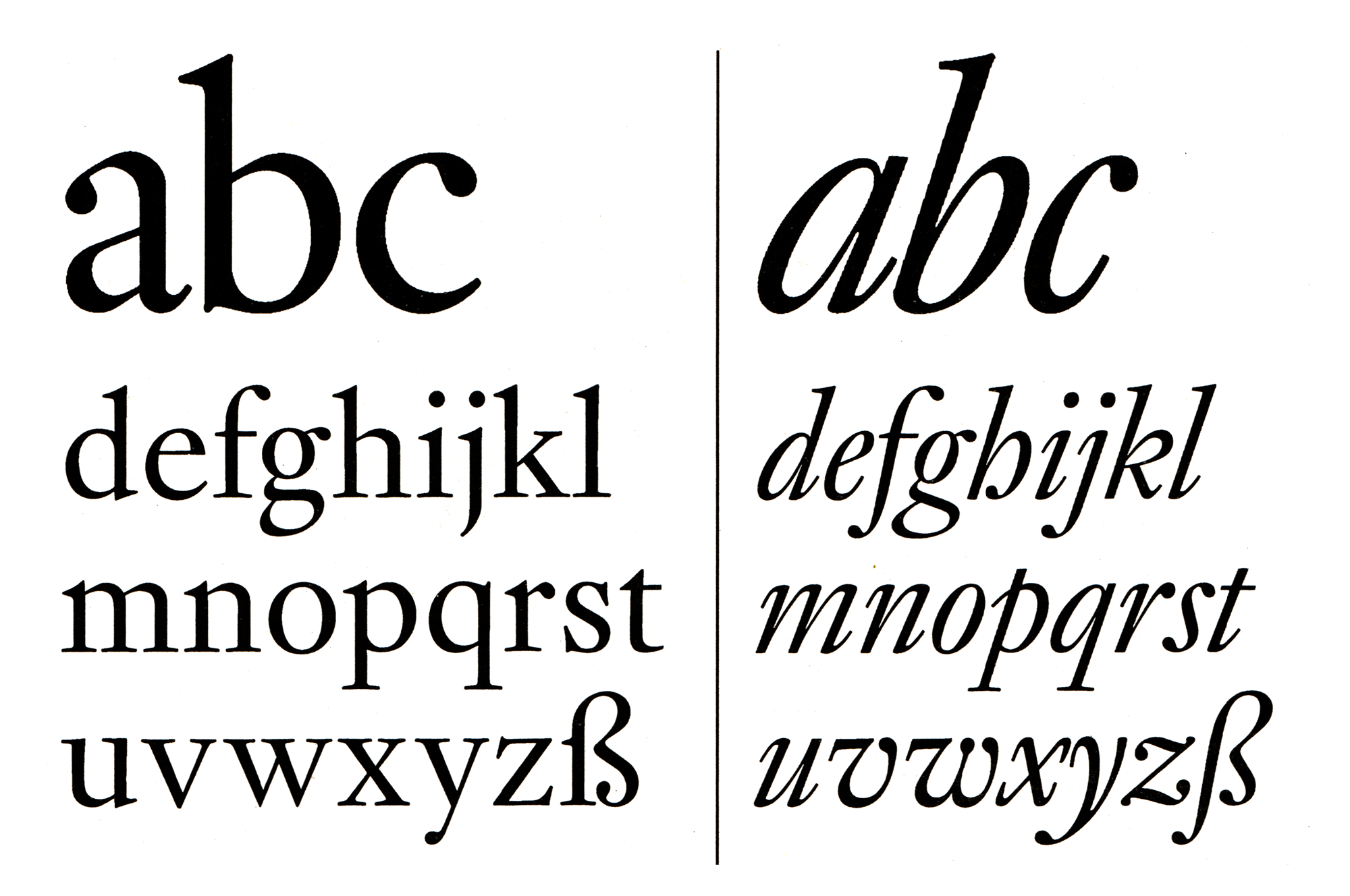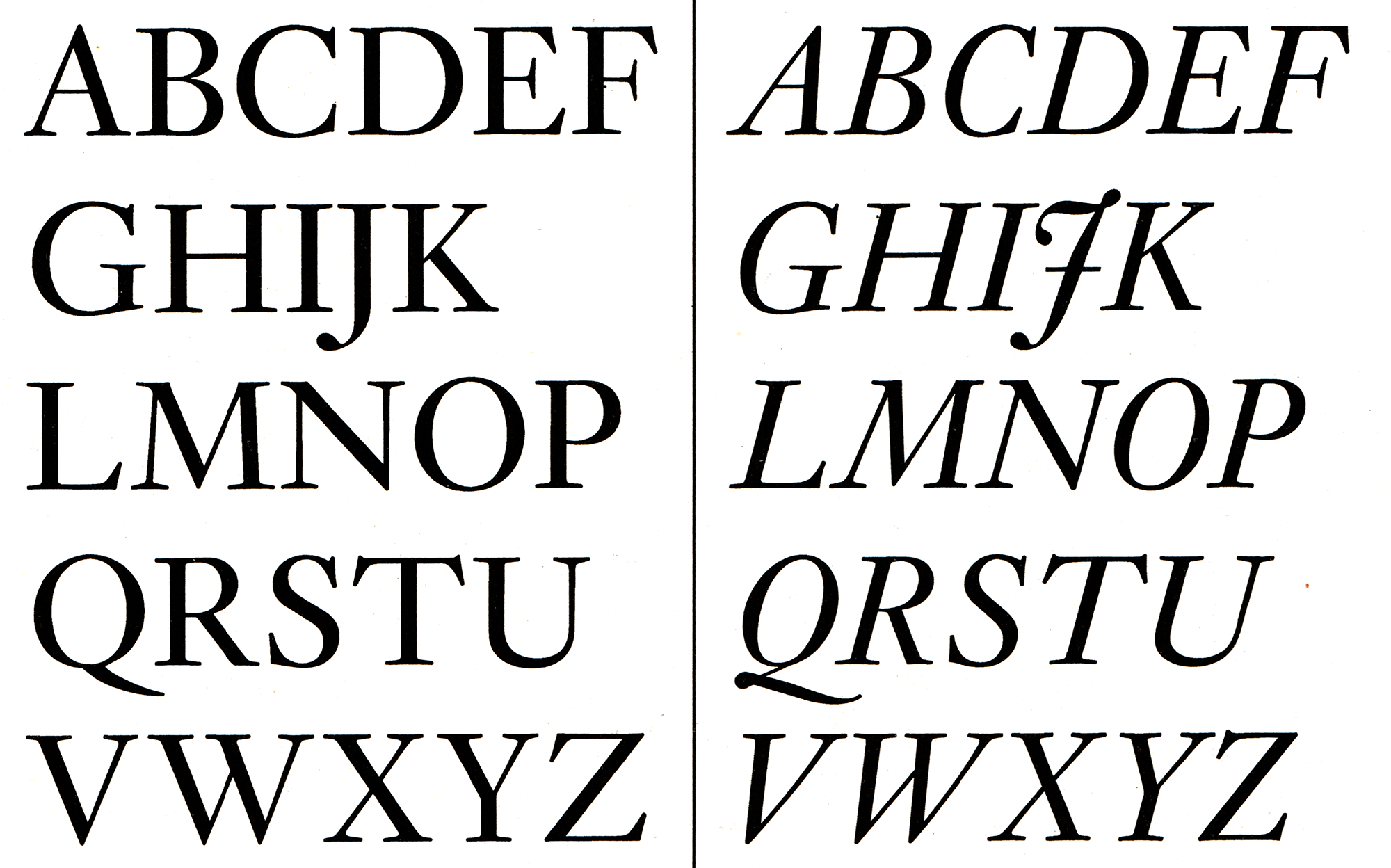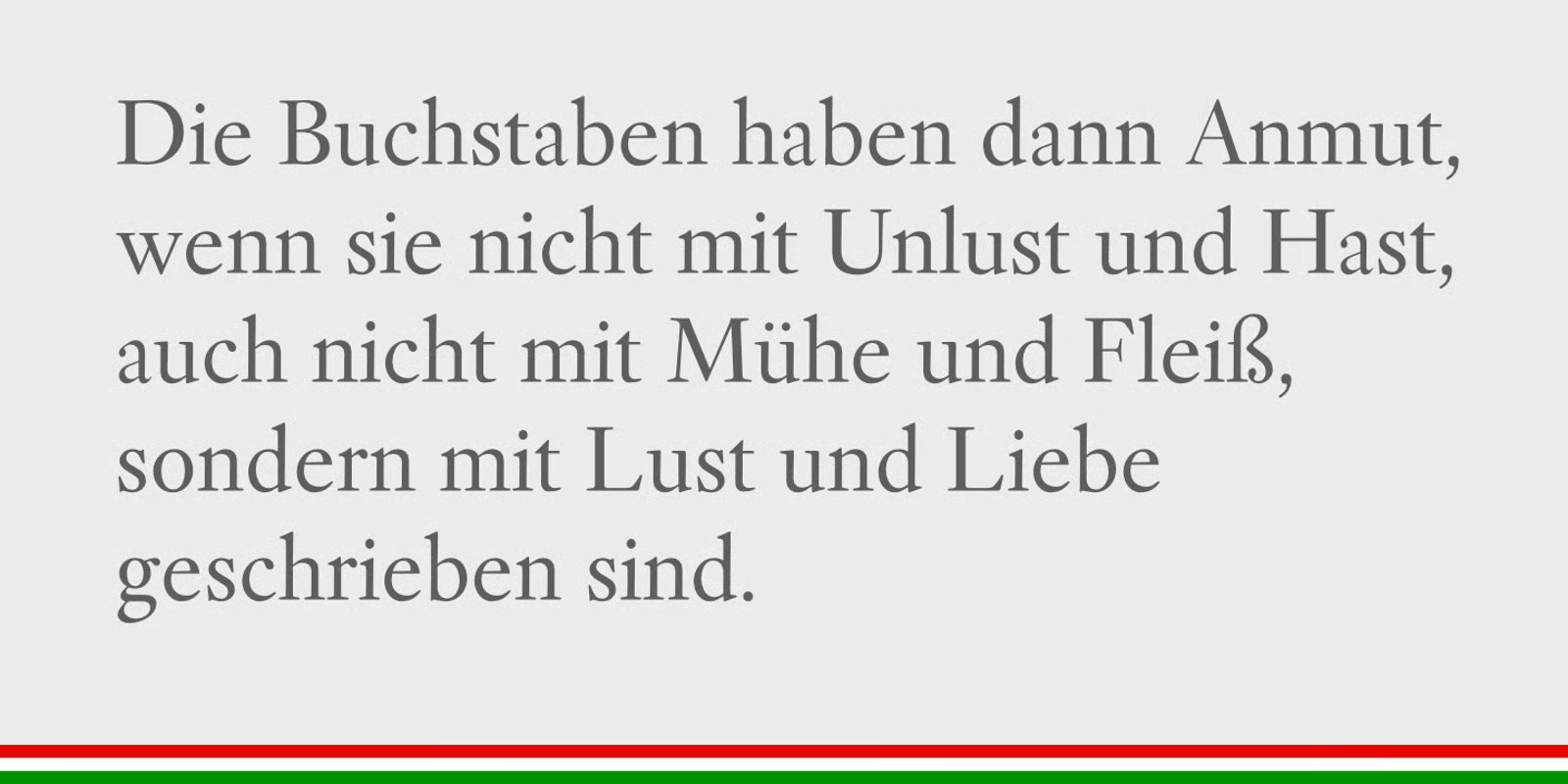
- Antiqua humanistisch
Die seit 1919 im Besitz von D. Stempel befindliche Janson Antiqua entwickelte sich im 20. Jahrhundert zu einer der beliebtesten Fließtextschriften. Doch die Zuschreibung zum Stempelschneider Anton Janson stellte sich durch weitere Nachforschungen schließlich als Fehler heraus. Als ihr Schöpfer gilt nun der ungarische Stempelschneider und Drucker Nicolas Kis. Der volkseigene DDR-Schriftanbieter Typoart veröffentlichte in den 1980er-Jahren die Typoart Kis in einer Überarbeitung für den Fotosatz. Prof. Dr. Albert Kapr beauftragte dazu die Leipziger Schriftgestalterin Hildegard Korger. Sie berichtet dazu:
»Werkzeuge und Material waren damals Stift, Pinsel, Temperafarbe, Karton. Die Versalhöhe der zu zeichnenden Figuren betrug 6 cm, davon abhängig war die Höhe der Minuskeln. Die Vorgaben entsprachen jenen, deren Realisierung schon Anfang der 70er Jahre zum Schriftwettbewerb der RGW-Länder (damalige »Ostblock«-Staaten) verlangt wurden: 18 Einheiten wie für Verwendung auf Monotype-Setzmaschinen, d.h. für die schmalsten Figuren »i« und »l« standen 5 Einheiten zur Verfügung, für die breitesten »M« und »W« 18 Einheiten. Gleichzeitig war das Prinzip der Linotype-Setzmaschine zu realisieren, was bedeutete, z. B. den Buchstaben »n« von Antiqua, Kursive und eventuell der Halbfetten auf die jeweils gleiche Breite (Kegeldickte) zu bringen. Es gab keine Überhänge und natürlich keinen Kursivkegel. Die Schrift sollte im Fotosatz für beide Systeme realisiert werden können. Ende der 60er Jahre hatte Tschichold seine Sabon nach diesem Prinzip gestaltet. Dass es unter Berücksichtigung solch technischer Einschränkungen außerordentlich schwierig war, dem Charakter einer historischen Renaissance- oder Barock-Kursiven gerecht zu werden, versteht sich von selbst.
Entsprechend dieser Vorgaben zeichnete ich die Buchtype mit Antiqua, Kursive, Kapitälchen, Versal- und Minuskelziffern, Sonderzeichen, Interpunktionen und allen Akzentbuchstaben. Im Prinzip war der Schriftentwurf fertig.
Die weitreichendste Neuerung im Type-Design war die ab seit 1978 bei Typoart eingeführte Digitalisierung der Entwurfszeichnung und die computergestützte Weiterverarbeitung der Schriftdaten. Nach und nach kam es zu einer Reihe technisch bedingter Veränderungen mit neuen Möglichkeiten für die Gestaltung. In deren Realisierung sah ich eine große Chance, mich dem Original der Kis zu nähern. Eine größere Anzahl an Einheiten stand jetzt zur Verfügung, nämlich 54 anstatt vorher 18. Der durch die Weiterführung des Linotype-Systems bedingte Zwang zur Übernahme der Antiqua-Kegeldickten für Kursive und Halbfette fiel weg. Für die Kursive konnte ein entsprechender Kursivkegel eingeführt werden. So genannte Überhänge ermöglichten es, Buchstabenteile auf den nächsten Kegel zu bringen. Damit war es möglich, Ober-, Unter- und Langlängen harmonischer zu gestalten, sogar mit Schwüngen auszustatten, wie sie für historische Schriften des späten 17. und frühen 18. Jahrhunderts durchaus typisch waren. Schließlich wurde die Anzahl der Einheiten so erweitert, dass sie für den Entwerfer keine Rolle mehr spielte.
Diese Änderungen wurden nach und nach eingeführt und in der Entwurfszeichnung realisiert. Zunehmend gewannen die Buchstaben der Kis mehr Authentizität, wurden charaktervoller, schöner. Trotzdem war ich nicht zufrieden. Infolge der vielen zeichnerischen Eingriffe fehlte es den Alphabeten nun an innerer Homogenität, an Harmonie; sie wirkten nicht mehr wie aus einem Guss.
Mit veränderter Konzeption fing ich nach einem Jahr Pause von vorne an. Ich hatte die Mittelhöhe reduziert. Dies und die »Befreiung« von den Einheiten ermöglichte es mir, auch die Proportionen in der Horizontalen zu verändern und einzelne Formen besser auszubilden. Ich hatte die Kis »gelernt«, beim Zeichnen klebte ich nicht mehr an den historischen Vorlagen.
Typoart konzipierte die Kis-Replik als Werksatzschrift, d. h. sie wurde, wie bei Typoart zu dieser Zeit üblich, in jeweils drei Basisgraden ausgeführt. Entgegen der bisherigen Praxis hatte ich den Entwurf für den 20pt Basisgrad gezeichnet. Von dieser Größe ausgehend wurden für den 9pt Basisgrad die Proportionen der Binnenräume breiter, offener gehalten und die Vor- und Nachbreiten der Buchstaben etwas erweitert. Die Mittelhöhe wurde ein wenig vergrößert, dünne Formteile ein wenig angefettet. Damit unterscheiden sich die Werkgrade deutlich von den Auszeichnungsgraden. Keinesfalls wäre ein befriedigendes Ergebnis nur durch mechanisches Verkleinern des Auszeichnungsgrades oder ein simples Vergrößern des Werkgrades zu erreichen gewesen. Für den 48pt Auszeichnungsgrad wurden die Vor- und Nachbreiten der Figuren etwas reduziert, die Buchstabenabstände dadurch enger. Das ist nötig, damit die Buchstabenfolge im Verbund des Wortes und im Verbund der Zeile nicht auseinander fällt oder wie gesperrt aussieht. Insgesamt ist die Laufweite der Typoart Kis Antiqua etwas größer gehalten als beim historischen Original.«
2006 beschloss Elsner+Flake, die Typoart Kis Antiqua von Hildegard Korger in überarbeiteter Form und erweitertem Umfang als OpenType-Pro-Variante herauszubringen. In den bei Elsner+Flake im IKARUS-Format vorhanden Datenbeständen aus dem Jahr 1989 waren vorhanden: Antiqua und Kursive mit Versal- und Minuskelziffern, Bruch- und Fußnotenziffern, (aufrechte) Kapitälchen, Punkturen, Akzente, Zeichen. Wie damals bei Typoart üblich, war die Schrift in den Größen von 9pt, 20pt und 48pt realisiert worden, was jeweils eine Modifizierung der im 20pt Grad angefertigten Ausgangszeichnung voraussetzte.
Nach Rücksprache mit Frau Korger beauftragte Elsner+Flake den Leipziger Schriftgestalter Erhard Kaiser mit der Durchführung der Überarbeitung. Zur Aufbereitung gehörte hier vor allem, die vorhandenen Daten von Unsauberkeiten an Form und Kontur zu befreien, die in der Vergangenheit etwa durch elektronische Konvertierungen entstanden waren. Diese zwischen 1984 und 1990 entstandene Typoart Kis findet sich mit neuer Zurichtung im jetzigen Headline-Schnitt wieder. Ausgehend von diesem Headline-Schnitt (TH Pro Regular und Italic) besteht die Schriftfamilie der Kis Antiqua Now aus dem Schnitt einer etwas kräftigeren Buchtype (TB Pro Regular und Italic) und einer deutlich fetteren Variante (TB Pro Semibold und Italic). Somit umfasst die Kis-Familie nun sechs Schnitte.
Eine weitere Digitalisierung in zwei Schnitten gibt es von RMU Fonts.
Fotosatz-Version
Neubearbeitung
RMU-Version